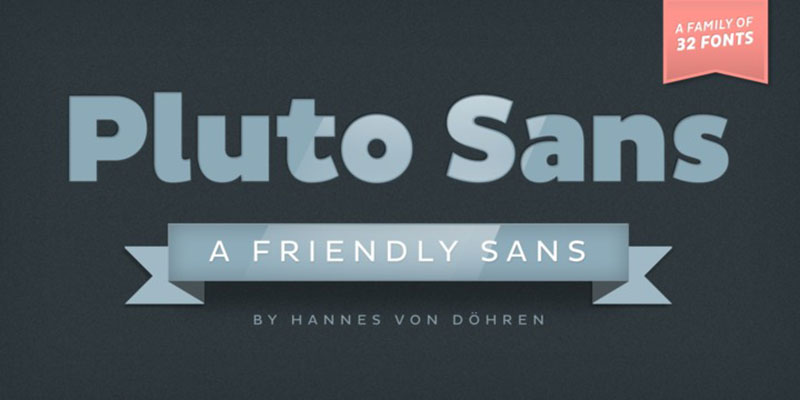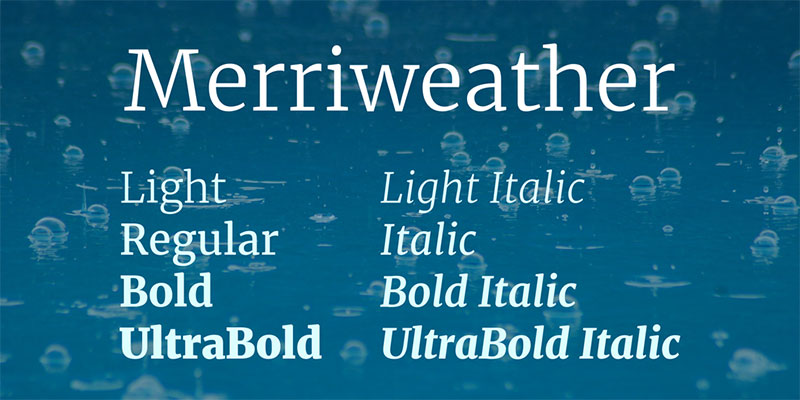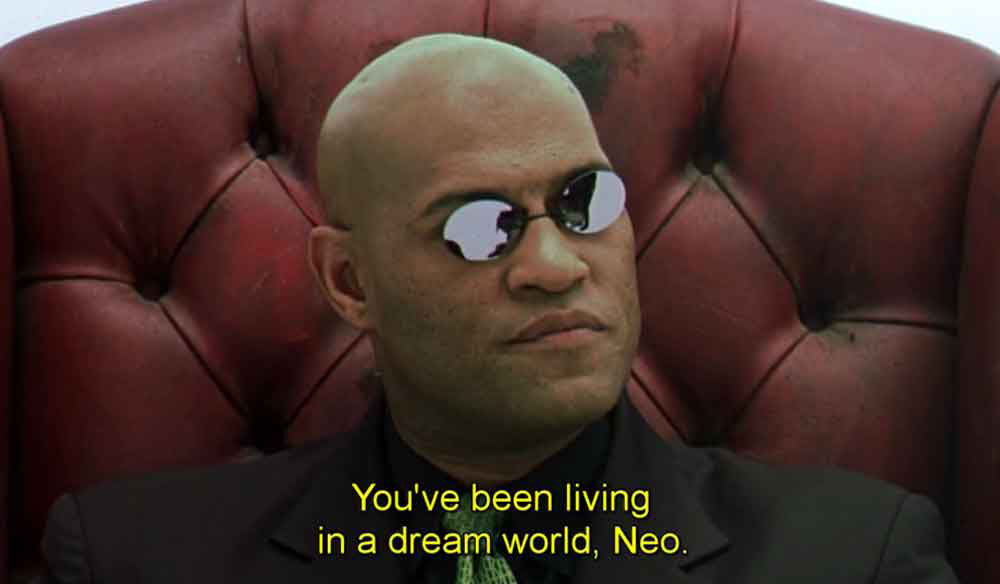
Stellen Sie sich Folgendes vor: Sie sind ganz vertieft in den neuesten Blockbuster, die Handlung wird immer spannender, aber oh, die Untertitel sind ein verschwommener Brei.
Frustration, nicht wahr? Deshalb ist die Auswahl der besten Schriftarten für Untertitel kein bloßer Designerspleen; sie ist entscheidend für ein immersives Seherlebnis.
Als Webdesigner habe ich gesehen, wie die richtige Schriftart Inhalte von gut zu großartig transformiert. In diesem Artikel tauchen wir in die Welt der Untertitelschriften ein.
Von den schlanken Linien der Sans Serif bis zum traditionellen Touch der Serif – die Schriftart beeinflusst die Lesbarkeit, Sichtbarkeit und sogar die Zugänglichkeit.
Wir sprechen nicht nur darüber, Wörter hübsch zu machen; es geht darum sicherzustellen, dass jeder, einschließlich Menschen mit Sehbehinderungen, auf dem Laufenden bleibt.
Sie lernen über Farbkontraste, optimale Untertitelgröße und wie verschiedene Bildschirme beeinflussen, was Sie sehen. Machen Sie sich bereit, Top-Schriftarten wie Arial, Helvetica und sogar spezialisierte wie Tiresias zu erkunden.
Am Ende wissen Sie genau, welche Schriftart Ihre Inhalte nicht nur lesbar, sondern auch unvergesslich macht.
Top empfohlene Schriftarten für Untertitel
| Schriftartenname | Serif/Sans-serif | Lesbarkeit | Abstand | Eigenschaften |
|---|---|---|---|---|
| Arial | Sans-serif | Hoch | Normal | Vielseitig, klar, sichere Wahl |
| Helvetica | Sans-serif | Hoch | Normal | Klassisch, professionell, weit verbreitet |
| Roboto | Sans-serif | Hoch | Normal | Modern, geometrisch, freundlich |
| Verdana | Sans-serif | Hoch | Weit | Klar, groß auf dem Bildschirm, gut für kleine Texte |
| Futura | Sans-serif | Moderat | Geräumig | Geometrisch, stilvoll, künstlerisch |
| Open Sans | Sans-serif | Hoch | Normal | Einfach, neutral, lesbar |
| Lato | Sans-serif | Hoch | Normal | Ausgewogen, warm, zugänglich |
| Tahoma | Sans-serif | Hoch | Normal | Klar für Bildschirmnutzung, ähnlich zu Verdana |
| Pluto Sans | Sans-serif | Hoch | Normal | Freundlich, klar, modern |
| Archivo | Sans-serif | Hoch | Straffer | Praktisch, starke Präsenz, leicht kondensiert |
| Times New Roman | Serif | Moderat | Normal | Traditionell, förmlich, Standard für Druck |
| Merriweather | Serif | Hoch | Normal | Lesbar, zeitgemäß, gut für lange Texte |
| Georgia | Serif | Hoch | Normal | Robust, elegant, großartig für Bildschirmlektüre |
| Times | Serif | Moderat | Normal | Klassisch, ähnlich wie Times New Roman, aber schmaler |
Sans Serif Schriftarten
Arial: Vielseitigkeit und häufige Verwendung
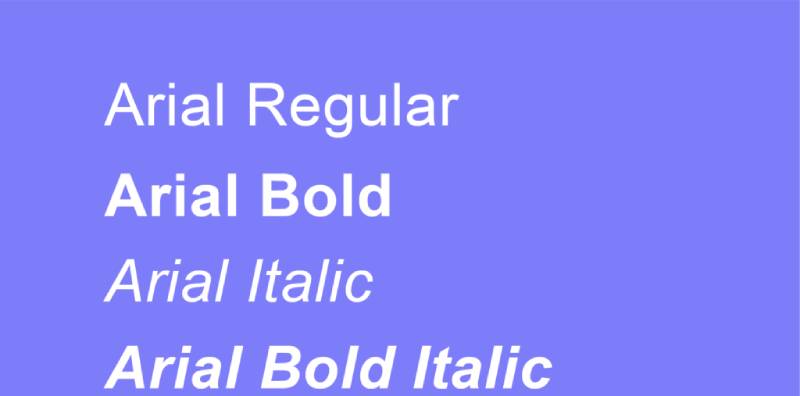
Arial, ach, Arial. Es ist wie der freundliche Nachbar unter den Schriftarten – bekannt, zuverlässig und überall zu sehen. Bekannt für seine Vielseitigkeit, ist Arial eine erste Wahl für Untertitel. Es ist klar, lesbar und versucht nicht, die Show zu stehlen. Perfekt für alles von YouTube-Videos bis zu Unternehmenspräsentationen.
Helvetica: Sauberes und poliertes Aussehen
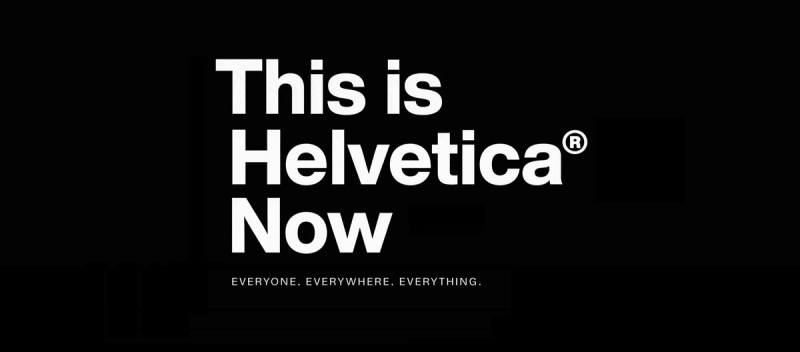
Als nächstes kommt Helvetica. Denken Sie an sie als die anspruchsvolle Cousine von Arial. Sie hat ein sauberes, poliertes Aussehen, das Professionalität ausstrahlt. Ideal für geschäftsbezogene Inhalte oder jede Situation, in der Sie möchten, dass Ihre Untertitel scharf und raffiniert aussehen. Es ist wie das Anziehen eines Anzugs für Ihren Text.
Roboto: Ideal für kleine Bildschirme
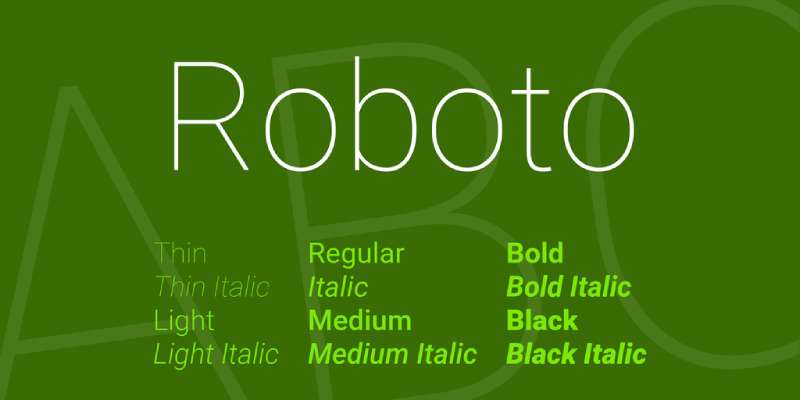
Jetzt sprechen wir über Roboto. Entwickelt mit Blick auf mobile Bildschirme, kommt es zur Geltung, wenn der Platz begrenzt ist. Klar, knackig und unkompliziert sorgt Roboto dafür, dass Ihre Untertitel auch auf den kleinsten Bildschirmen angenehm für die Augen sind.
Verdana: Lesbarkeit bei kleinen Größen
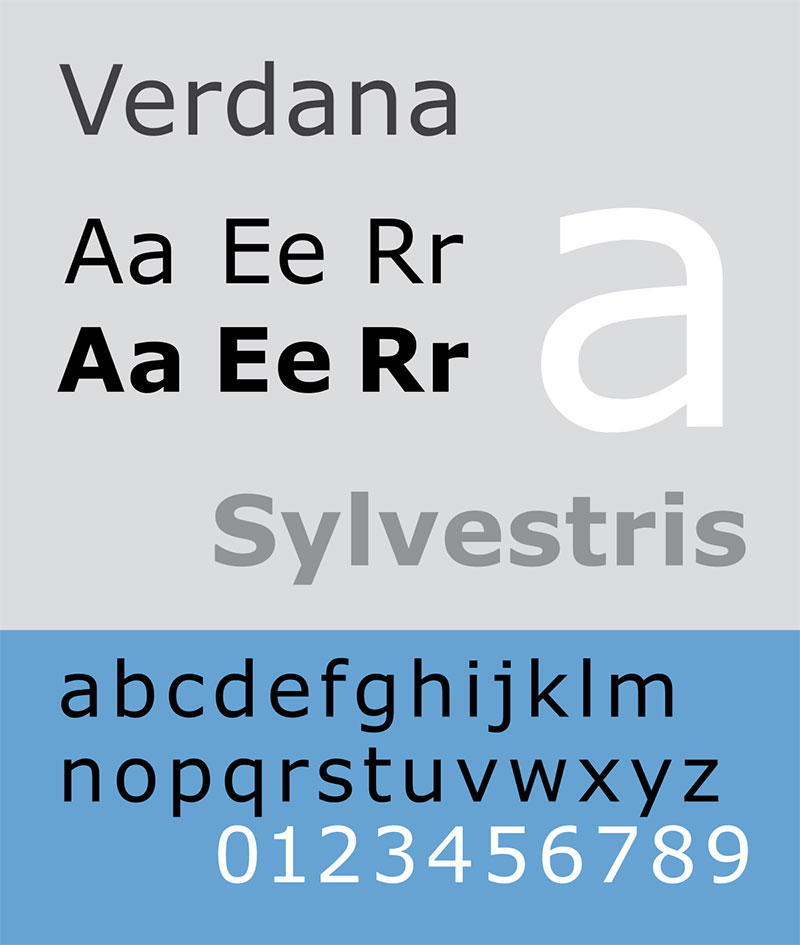
Verdana, der Held für winzige Texte. Wenn Ihr Inhalt wahrscheinlich auf kleineren Bildschirmen angesehen wird, ist Verdana Ihre Schriftart. Sie ist so konzipiert, dass sie auch in kleinen Größen lesbar ist, sodass selbst auf einem Smartphone diese Untertitel kein verschwommener Fleck sind.
Futura: Vermittlung von Modernismus und Futurismus
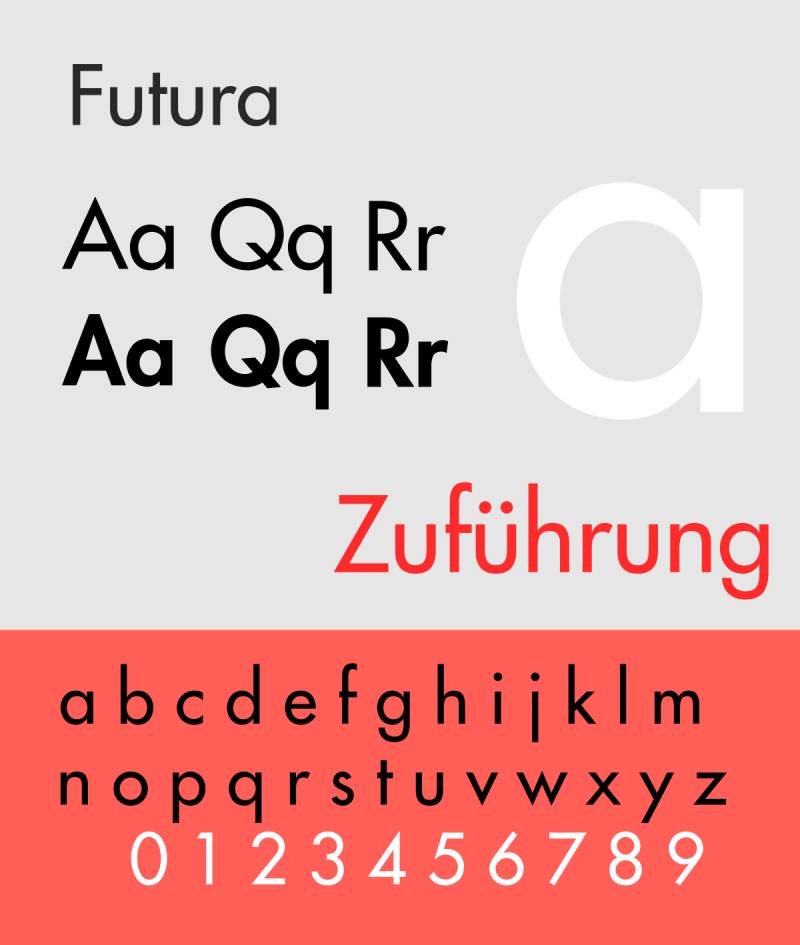
Futura tritt mit einem Hauch von Modernismus auf. Seine geometrischen Formen und gleichmäßigen Striche verleihen ihm ein futuristisches Gefühl. Es ist nicht nur eine Schriftart; es ist eine Aussage. Ideal für Inhalte, die eine topaktuelle oder künstlerische Atmosphäre vermitteln wollen.
Open Sans: Humanistische Sans Serif, gut für Video und Druck
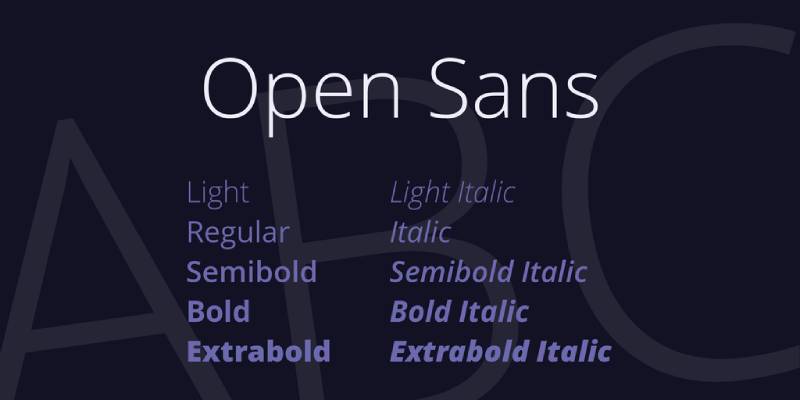
Open Sans ist wie ein Multitalent. Es ist freundlich und lesbar, was es sowohl für Untertitel in Videos als auch für gedruckten Text großartig macht. Es ist die Art von Schriftart, die sagt: „Hey, ich bin einfach zu lesen, aber trotzdem cool.“
Lato: Elegant und unternehmerisch ansprechend
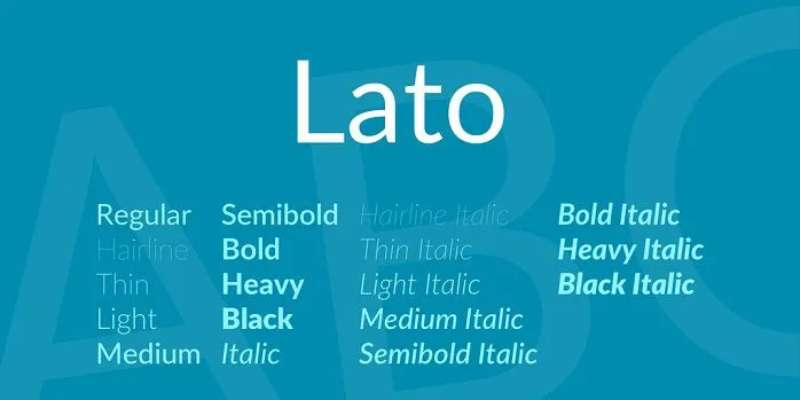
Lato bringt Eleganz mit. Mit seinen halbrunden Details und eleganten Linien ist es perfekt für Inhalte geeignet, die eine Prise Raffinesse benötigen, ohne übertrieben zu wirken. Es ist unternehmerisch, aber mit einem Dreh.